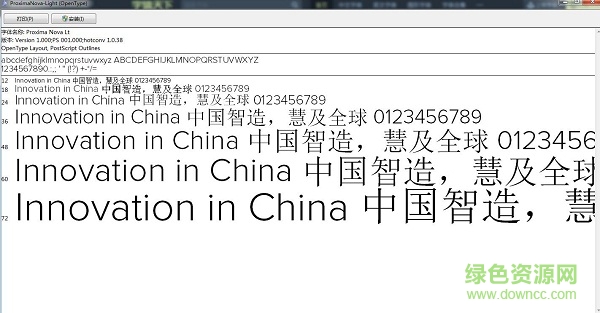
proximanova-light字體是一款簡(jiǎn)潔、清晰且纖細(xì)的英文無(wú)襯線字體,該字體沒(méi)有多余設(shè)計(jì),筆畫(huà)垂直,干凈無(wú)累贅,給人冷靜客觀的感覺(jué),歡迎大家免費(fèi)下載!
1.現(xiàn)代Sanserif的起源并不算很久,也就100多年的歷史。沒(méi)有裝飾的成份,具有較好的可讀性成為它的最大武器。
2.起初由于它那打破傳統(tǒng)的前衛(wèi)造型,而被保守人士所排斥,在德國(guó)它更因此被稱(chēng)做Grotesque(意即丑陋的)。
3.當(dāng)它被傳入美國(guó)時(shí)被誤解為歌德體,至今仍被稱(chēng)做Gothic。
4.隨著現(xiàn)代設(shè)計(jì)的發(fā)展,Sanserif字體已被廣泛的為大家所熟識(shí)和使用。